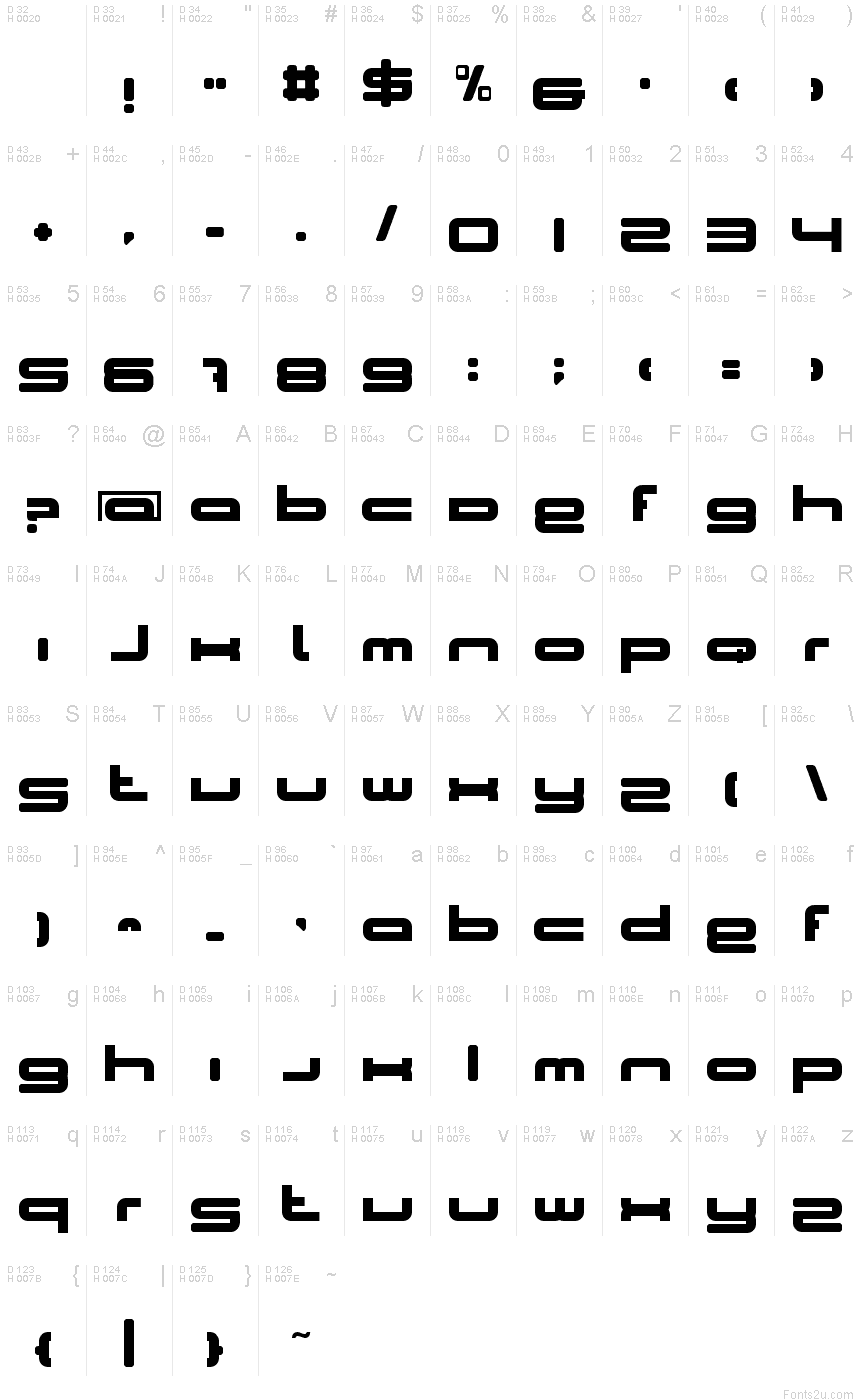
BN Cosmic Girl
BN Cosmic Girl autorstwa Bena Nathana to bezpłatny, nowoczesny krój displayowy o wyrazistym, kosmicznym charakterze. Szerokie, kwadratowe łuki i miękkie narożniki tworzą odważną, niemal gumową teksturę, a poziome wycięcia nadają każdej literze elegancki, sci-fi połysk. Zwarty i równy rytm sprawia, że słowa łączą się ze sobą niczym moduły na kadłubie statku kosmicznego, dzięki czemu Twoje nagłówki wyglądają jak precyzyjnie zaprojektowane, a nie improwizowane.
Dzięki BN Cosmic Girl nadasz futurystycznego sznytu brandingowi, logotypom gier, okładkom muzyki elektronicznej, tytułom filmów, plakatom konferencji technologicznych i śmiałym nagłówkom UI, wprowadzając je w klimat retro-futuryzmu. Ten bezpłatny font najlepiej sprawdza się w większych rozmiarach, gdzie jego wewnętrzne pasy są wyraźnie widoczne; w tekstach głównych połącz go z lekkim, geometrycznym krojem bezszeryfowym, aby zachować ostrość i czytelność całego projektu.